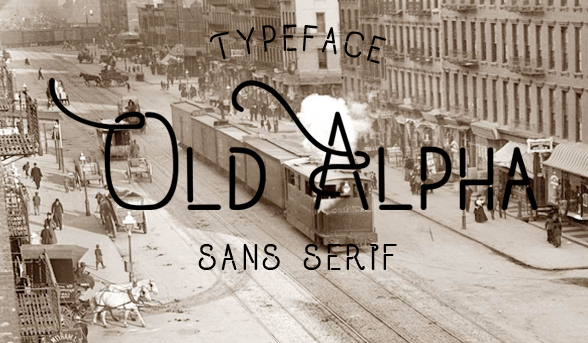
Old Alpha Typeface – Fonte Grátis
Old Alpha Typeface
A Old Alpha Typeface é uma fonte sans-serif inspirada nos estilos clássico e vintage, perfeita para criar qualquer tipo de layout visual. Seu design limpo e elegante torna-a ideal tanto para marcas de marca quanto para embalagens de produto, cartas de convite, cartazes e camisetas customizadas com citações. Esta é uma versão gratuita da fonte, mas para ter acesso ao conjunto completo, basta clicar no link abaixo e visitar o meu store para explorar mais belas fontes disponíveis: https://fontbundles.net/anggunsuandewi ou https://creativemarket.com/madeDeduk. Quanto mais compartilharmos estas maravilhas criativas, melhor será para todos nós. Estamos sempre à disposição para ajudá-lo a transformar ideias em arte digital com as nossas fontes!